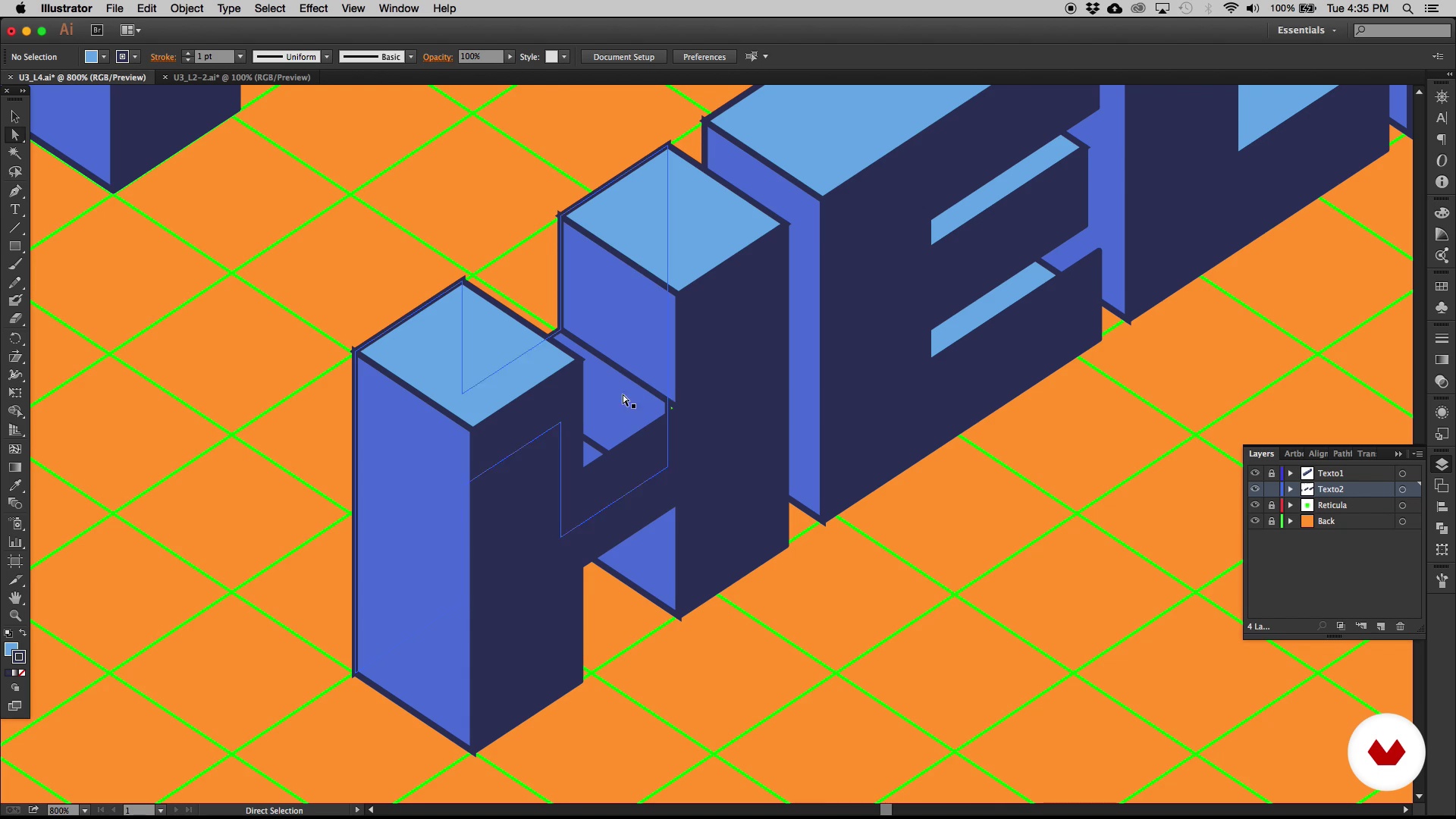
Illustration vectorielle isométrique à partir de zéro
Typographie P1
À propos de la leçon : Typographie P1
“Dans cette leçon, nous allons apprendre à travailler la typographie, à l'utiliser comme élément dans nos compositions. Nous allons d'abord créer un mot auquel nous ajouterons du volume et appliquerons les principes d'éclairage que nous avons déjà appris pour créer un effet 3D.”
Dans cette leçon, Jorsh Peña aborde le sujet : Typographie P1, qui fait partie du cours Domestika en ligne : Illustration vectorielle isométrique à partir de zéro. Apprenez les techniques de base pour créer des compositions vectorielles avec Adobe Illustrator.
“UNITÉ 3 Typographie Partie 1 Dans cette leçon, nous verrons comment modifier notre typographie avec des perspectives différentes pour coexister avec nos éléments et faire partie de la composition finale. Nous allons le faire. Je vous donne des exemples de ce que nous pouvons créer avec une grille. Nous avons ce type de texte. Ils sont simples mais ils nous aident à avoir une meilleure esthétique. Nous pouvons convertir une police en un élément et cela nous aidera à donner un sens différent à la composition. Nous allons commencer par quelques exemples cela nous aidera à développer cette tech...”